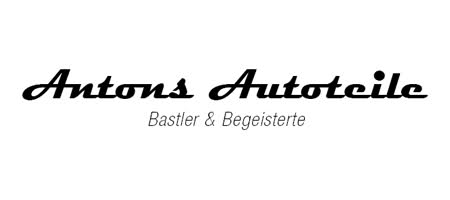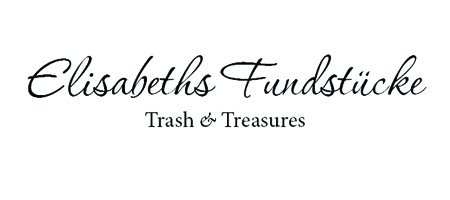
Schriftart für Tattoo-Studio ?
Hi, ich suche eine Schriftart für ein Tattoo-Studio (traditioneller Laden, existiert seit über 20 Jahren, nicht festgelegt auf z.B. "nur asiatisches" oder "nur oldstyle"). Es gab da mal so eine Neon-Reklame "Tattoo", war so eine Schrift im Western(?)-Stil, weiss jemand was ich meine - oder hat jemand eine Idee, was da für ein Font passen könnte ?
Eine Schriftart für eine Wortmarke, oder für Fließtext?
Generell sollte sich die Schrift nach dem Laden richten, verbann einfach mal das Wort »Tattoo« kurzzeitig aus Deinen Gedanken;
Wie ist der Inhaber drauf?
Wie alt?
Berufen, oder Tätowierer weil ihm nix besseres eingefallen ist?
Was springen da sonst noch für Angestellte rum?
Wo ist der Laden, und wie ist er eingerichtet?
Welche Kunden will er ansprechen? Mädels die grad 18 geworden sind und unbedingt einen Delphin auf der Stirn brauchen, halbwegs Vernunftbegabte Leute die beraten werden wollen, ob ein Tattoo zu ihnen passt, oder die Hardcorefreaks bei denen man erstmal noch ein Stück freie Haut suchen muss?
Das sind Fragen die Du einerseits selbst mal objektiv beantworten solltest, so weit das geht, und die Du dann vor allem auch dem Tattookünstler stellen musst. Verlier nicht aus den Augen, dass es zwar an sich alles gut aussehen muss und nach den entsprechenden Regeln aufgebaut, dass das Design aber (mindestens genauso wichtig) verschiedene Zwecke erfüllen soll: Etwas darstellen, und zwar idealerweise nix erlogenes, weil das die Kunden enttäuscht, aber durchaus am oberen Rand des unter diesem Gesichtspunkt noch zulässigen, damit Dein Kunde auch was davon hat. Und Kunden anziehen (niemand braucht ne Schrift am Laden weils schön aussieht, da kann man auch nen Benz davor parken ... ), und zwar die richtigen.
Den Ansatz solltest Du mal verfolgen, dann kommen Dir ganz von allein brauchbare Ideen, respektive kannst Du mit den gewonnenen Infos leichter nach weiteren Möglichkeiten forschen und fragen; Du brauchst ein möglichst detailiertes Bild vom Kunden bei Dir im Kopf, bevor Du ihm mit einer Gestaltung helfen kannst :D
Na, ich finde das steht in meiner Frage: "Seit über 20 Jahren traditionelles Studio", was soll die Frage "Tätowierer weil ihm nix besseres eingefallen ist" ?
Der Laden ist in einer deutschen Gross-Stadt, sehr etabliert, nur Profis am Start, vielseitig, Tattoos von bunt über schwarzweiss, von asiatisch und oldstyle bis newschool, nun soll eben der Laden renoviert werden und dabei sollen auch neues Briefpapier, neue Visitenkarten, neue Flyer und ein neuer Schriftzug auf's Schaufenster.
Der Name bezieht sich nicht auf irgendwas (wie z.B. "Dragon-Tattoo" oder "Freibeuter Tattoo", da würde mir auch selber was einfallen) - der Laden heisst einfach "stadtname" Tattoo & Piercing, die Schriftart sollte auch eher Bezug zum Thema Tattoo haben als zur Stadt, wo es sich befindet. Also schon was "hübsches", nicht zu verspielt, bei einem im Durchschnitt 50-jährigen Team also auch eher was "traditionelles" (so wurde MIR das erklärt, bin aber selbst kein Designer oder sowas, mache aber die Webseite von denen und würde dann eben auch ein paar Flyer usw. mit für die Jungs erstellen, wegen "Schrift" dachte ich, ich frag' mal hier die Profis im Forum).......... :)
Na, ich finde das steht in meiner Frage: "Seit über 20 Jahren traditionelles Studio", was soll die Frage "Tätowierer weil ihm nix besseres eingefallen ist" ?
Und nein, die Informationen die wichtig sind gingen aus Deinem Post leider nicht so ausführlich hervor, wie das notwendig ist, um eine Empfehlung auszusprechen und die auch vernünftig begründen zu können :? Ich habe mit meiner Antwort versucht das klar zu machen und Dir gleich einige der wichtigeren Fragen an die Hand zu geben, denn ...
bin aber selbst kein Designer oder sowas, mache aber die Webseite von denen und würde dann eben auch ein paar Flyer usw. mit für die Jungs erstellen, wegen "Schrift" dachte ich, ich frag' mal hier die Profis im Forum).......... :)
... ungefähr so oder so ähnlich hatte ich mir die Situation vorgestellt. Zu einem/r guten Firmenidentität/Branding/Corporate Design, wie auch immer Du es gerne nennen möchtest, gehört eben mehr als ein, zwei Stichworte und dann ne Schrift raussuchen - das ist eher das kleinere Problem. Das ist jetzt auch nicht böse gemeint, sondern ich versuche Dir ganz grob zu umreißen, was Du tun musst um Deinem Klienten wirklich zu helfen: Beim Webdesign muss man ja auch viel mehr wissen und können als ein Bisschen HTML/CSS/Flash/Java, brauch ich Dir ja nicht zu erzählen :D Und hier ist es auch nicht anders; schön aussehen hilft nix, wenn die Seite in Google nicht gut gefunden wird, langsam lädt, zig Plugins braucht die kaum jemand installiert hat, was weiß ich :D Und Logo, Flyer, Schaufenster, Geschäftskarte etc. helfen nicht, wenn sie nicht kommunizieren: Sie brauchen eine Aussage (wer ist der Klient, was tut er, was will er vom Betrachter [n Tatto verkaufen], was ist der Nutzen für den Kunden [warum hier und nicht woanders stechen lassen?] blah blah) und müssen gezielt sein. Also musst Du wissen mit wem Du überhaupt kommunizieren willst, daher meine Frage nach der Kundschaft, und musst die Kommunikation dann so gestalten, dass sie die Botschaft vermittelt und die richtigen Leute anspricht.
Ergo musst Du das Deinen Klienten vorher alles mal fragen :D
Der Laden ist in einer deutschen Großstadt, sehr etabliert, nur Profis am Start, vielseitig, Tattoos von bunt über schwarzweiss, von asiatisch und oldstyle bis newschool, nun soll eben der Laden renoviert werden und dabei sollen auch neues Briefpapier, neue Visitenkarten, neue Flyer und ein neuer Schriftzug auf's Schaufenster.
Der Name bezieht sich nicht auf irgendwas (wie z.B. "Dragon-Tattoo" oder "Freibeuter Tattoo", da würde mir auch selber was einfallen) - der Laden heisst einfach "stadtname" Tattoo & Piercing, die Schriftart sollte auch eher Bezug zum Thema Tattoo haben als zur Stadt, wo es sich befindet. Also schon was "hübsches", nicht zu verspielt, bei einem im Durchschnitt 50-jährigen Team also auch eher was "traditionelles" (so wurde MIR das erklärt,